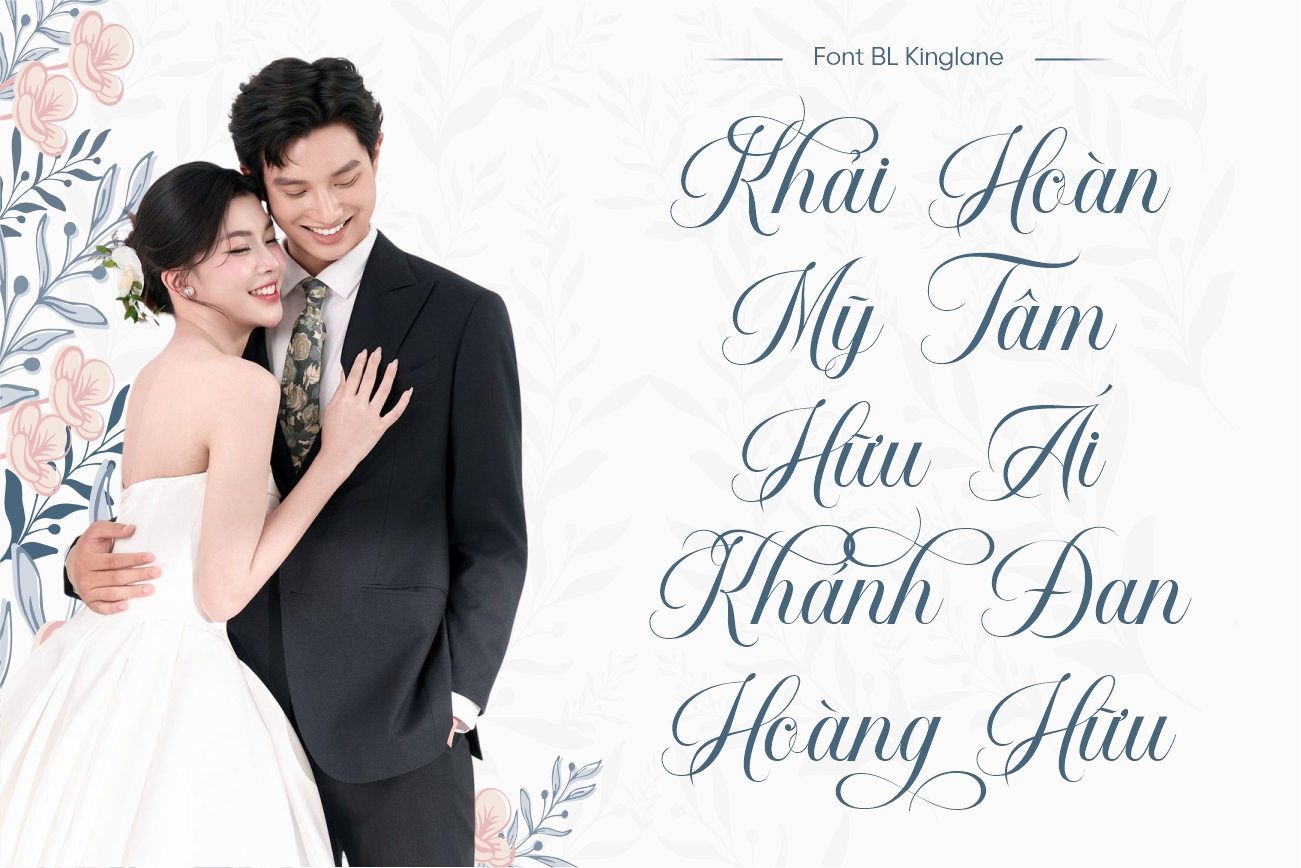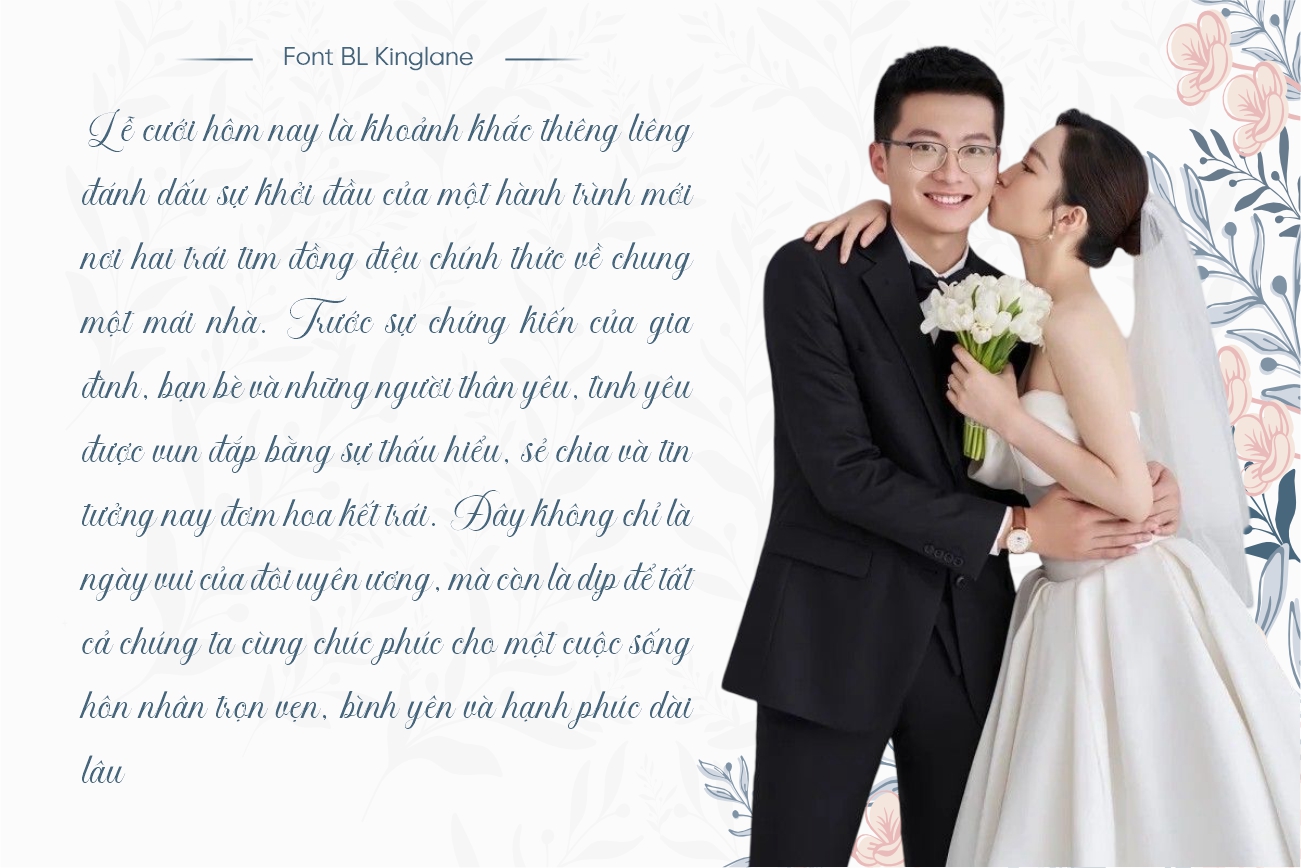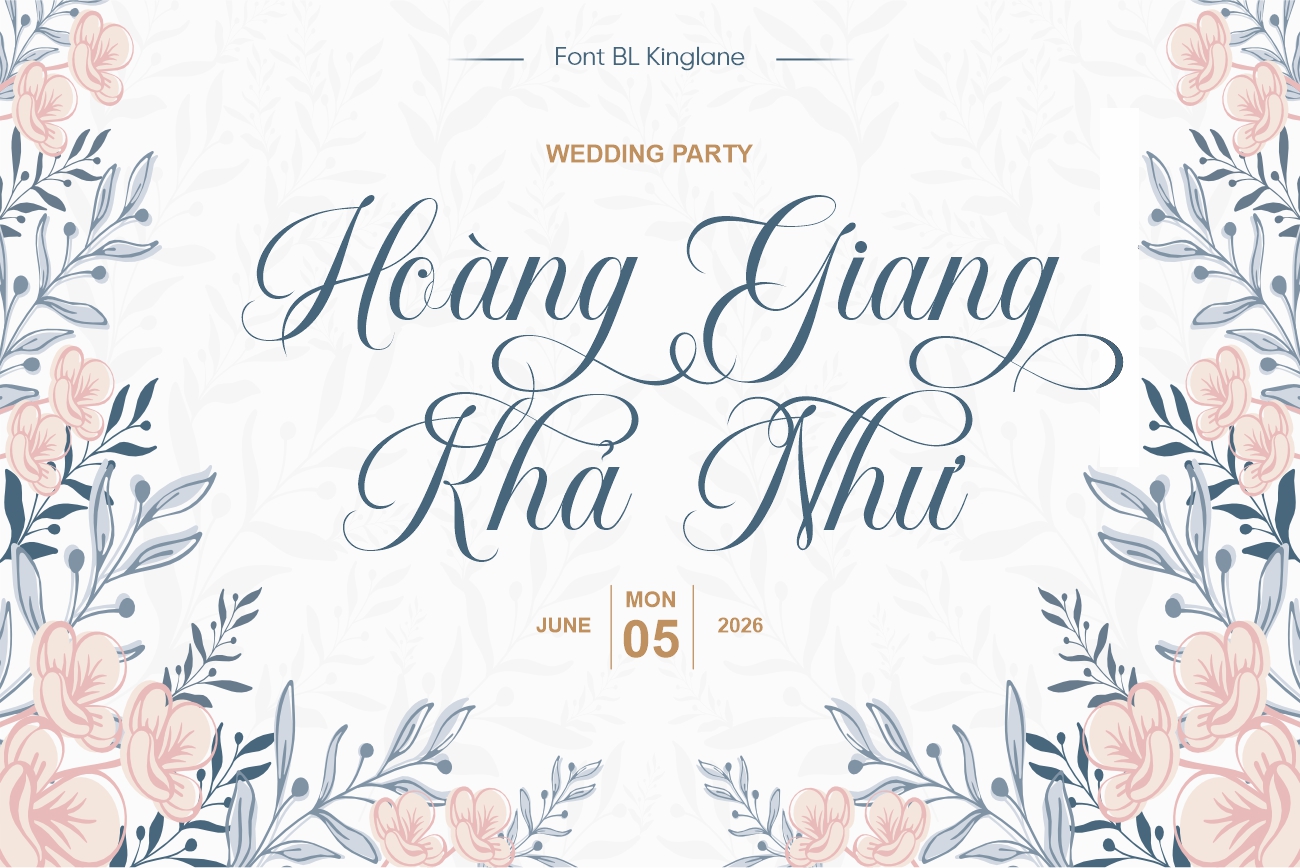
BL Kinglane - Font chữ thiệp cưới thanh lịch và độc đáo
Tác giả Muhammad Nazar
Việt hóa Font BL
BL Kinglane là phiên bản Việt hóa từ bộ font Kinglane Script do Muhammad Nazar thiết kế, mang đậm tinh thần lãng mạn và tinh tế của phong cách chữ viết tay cổ điển. Ngay từ cái nhìn đầu tiên, bộ chữ tạo cảm giác mềm mại, duyên dáng và đầy cảm xúc, rất phù hợp với những thiết kế cần sự nhẹ nhàng và trang nhã. Team BL đã thực hiện quá trình Việt hóa một cách kỹ lưỡng, đảm bảo hệ thống dấu tiếng Việt hiển thị mượt mà, cân đối và liền mạch, giúp BL Kinglane dễ dàng ứng dụng trong các dự án thiết kế tại Việt Nam mà vẫn giữ trọn vẻ đẹp nguyên bản của font gốc.
Về kiểu dáng, BL Kinglane sở hữu những đường nét uốn lượn nhẹ nhàng, mềm mại và có nhịp điệu tự nhiên, tạo nên cảm giác font thiệp cưới mượt mà, sạch sẽ và rất dễ nhìn. Các nét chữ được xử lý tinh gọn, không quá cầu kỳ nhưng vẫn đủ tinh tế để toát lên vẻ nữ tính, gợi cảm, quyến rũ một cách nhẹ nhàng và sang trọng. Chính sự tiết chế trong thiết kế giúp bộ chữ trở nên đơn giản và dễ đọc, phù hợp cho cả tiêu đề lẫn nội dung ngắn, đặc biệt hiệu quả khi sử dụng trên thiệp cưới, thiệp mời, bảng tên, menu tiệc cưới hoặc các ấn phẩm trang trí mang không khí lãng mạn.
BL Kinglane mang rõ dấu ấn của phong cách cổ điển, gợi nhớ đến những dòng chữ viết tay thanh lịch của các thiết kế truyền thống, nhưng vẫn đủ tinh chỉnh để phù hợp với thẩm mỹ hiện đại. Nhờ đó, font không chỉ giới hạn trong lĩnh vực cưới hỏi mà còn có thể ứng dụng linh hoạt cho thiệp chúc mừng, thương hiệu thời trang nữ, mỹ phẩm, logo cá nhân hoặc các dự án cần truyền tải sự dịu dàng và cảm xúc. Khi đặt trong bố cục tổng thể, BL Kinglane giúp nội dung trở nên mềm mại hơn, tạo thiện cảm và cảm giác gần gũi cho người xem.
Nguồn gốc của Kinglane Script bắt nguồn từ cảm hứng về vẻ đẹp cổ điển và sự lãng mạn vượt thời gian trong nghệ thuật chữ viết tay. Khi được Team BL Việt hóa thành BL Kinglane, bộ font không chỉ giữ nguyên tinh thần thiết kế của Muhammad Nazar mà còn trở nên thân thiện và dễ sử dụng hơn với tiếng Việt. Nếu bạn đang tìm kiếm một font thiệp cưới mượt mà, sạch sẽ, nữ tính, mang nét gợi cảm, quyến rũ, đơn giản và dễ đọc theo phong cách cổ điển, BL Kinglane chắc chắn sẽ là lựa chọn lý tưởng để tạo nên những thiết kế tinh tế, giàu cảm xúc và đầy dấu ấn riêng.